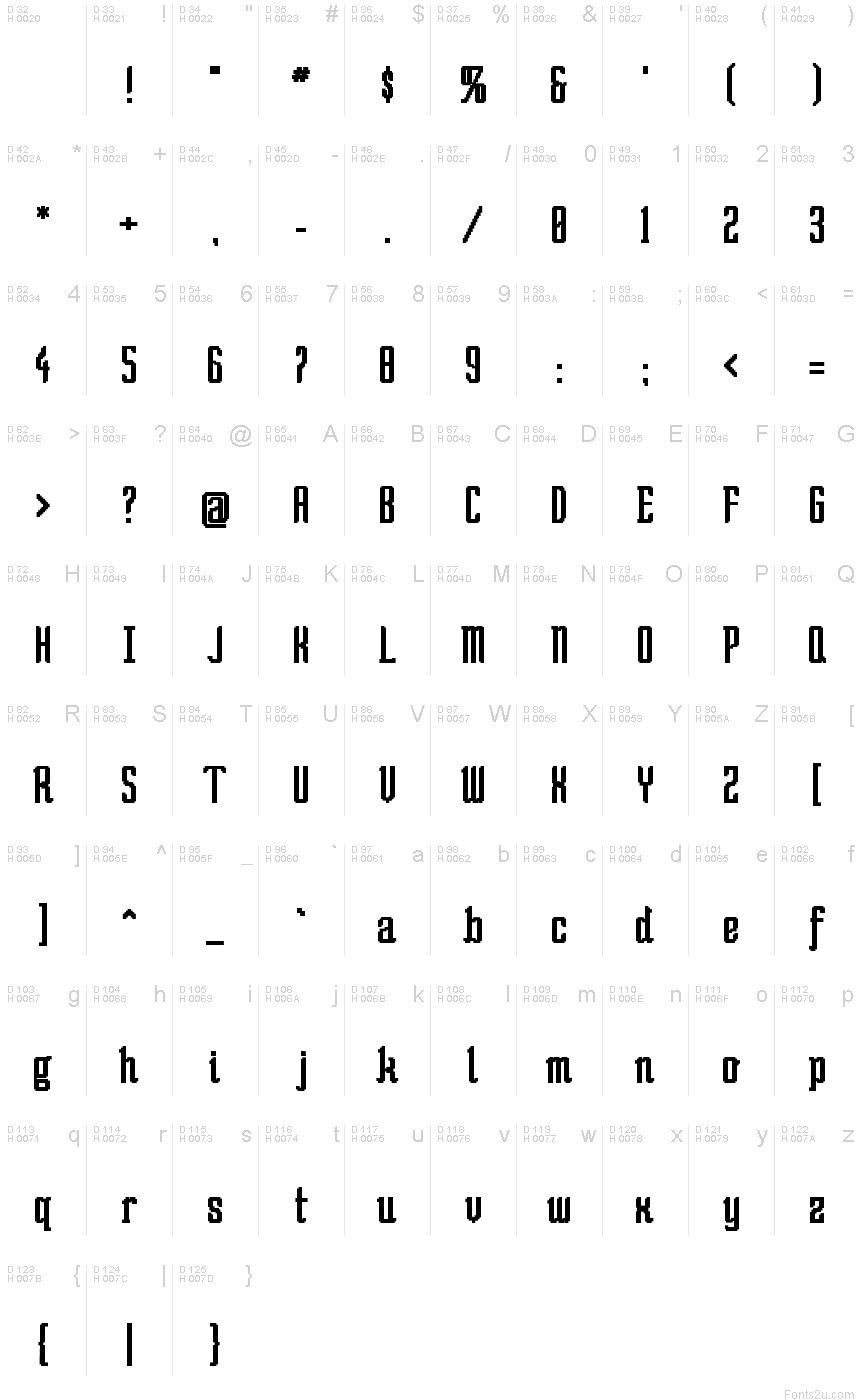
So Bad, od Apostrophic Labs, to bezpłatny bitmapowy font typu blackletter, który serwuje surowe, cyfrowe spojrzenie na tradycyjne gotyckie liternictwo. Znaki są wysokie i ostre, łącząc średniowieczny klimat z grubymi pikselami, co nadaje fakturze wyrazisty, nieco niepokorny charakter.
Świetnie sprawdzi się w tytułach gier retro, na okładkach zinów, plakatach, logotypach zespołów czy nastrojowych banerach internetowych, gdzie darmowy font ma budować mroczny, lo-fi klimat, unikając przy tym zbytniej gładkości. Dzięki uproszczeniu gotyckich kształtów do formy blokowych pikseli, font doskonale nadaje się do krótkich tytułów i napisów, które potrzebują średniowiecznego sznytu połączonego z surowością wczesnej ery cyfrowej.